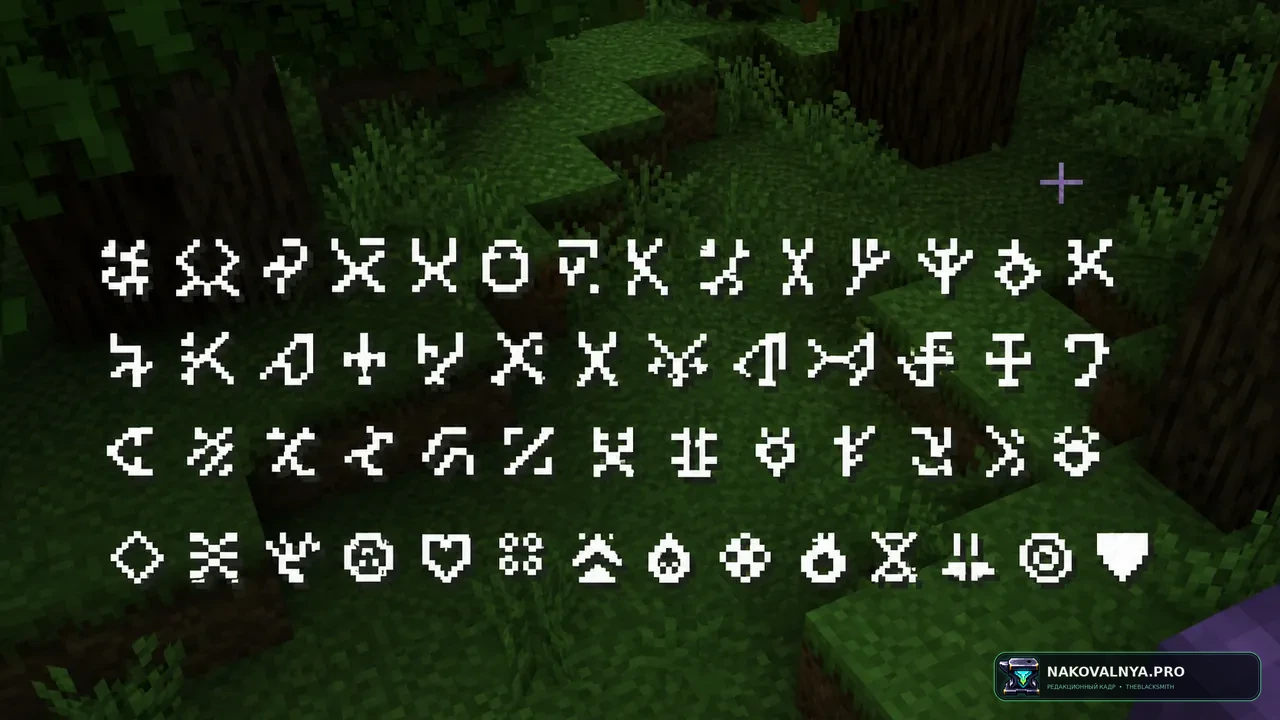
Slightly Improved Font (32x) — текстуры на улучшенный ванильный шрифт в МайнкрафтеВместо полной замены типографики автор берёт оригинальный шрифт за основу и перерисовывает его в удвоенном масштабе. Поэтому меню и сообщения остаются сразу узнаваемыми, но контуры символов выглядят более проработанными. Поддержка Unicode расширяет пользу за пределы базового латинского набора и важна для многоязычного текста, имён и серверных сообщений. Узкая специализация позволяет использовать пакет поверх почти любого оформления: он не навязывает новую палитру, иконки или рамки окон. Это удобный последний слой для сборки ресурсов, где визуальный мир уже настроен отдельно.
Стоит выбрать игрокам, которым нравится ванильная типографика, но хочется более аккуратной 32-пиксельной отрисовки и Unicode. Не подойдёт тем, кто ищет радикально новый шрифт или комплексный редизайн меню.
Ванильный шрифт Minecraft.
Шрифт заново отрисован в 32x.
Да, она прямо заявлена автором.